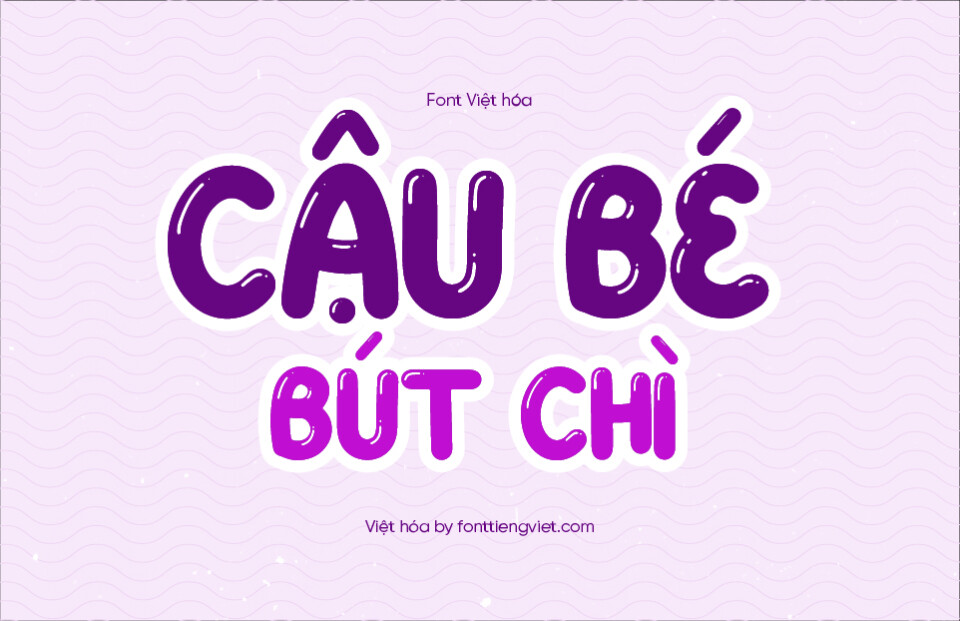
Font Việt hóa 1FTV VIP Balloon Dreams – Font bong bóng
Font Việt hóa 1FTV VIP Balloon Dreams – Font bong bóng cho thiết kế sáng tạo
Giới thiệu về Font Việt hóa 1FTV VIP Balloon Dreams – Font bong bóng
Trong thế giới đồ họa hiện đại, việc tìm kiếm một Font Miễn Phí mang phong cách vui nhộn và trẻ trung luôn là ưu tiên hàng đầu của các nhà thiết kế. Font Việt hóa 1FTV VIP Balloon Dreams – Font bong bóng là một lựa chọn hoàn hảo, mang đến hơi thở mới lạ với những đường nét mô phỏng hình dáng của những quả bong bóng căng tròn. Bộ font này không chỉ dừng lại ở tính thẩm mỹ mà còn được tối ưu hóa hoàn toàn cho tiếng Việt, giúp người dùng dễ dàng truyền tải thông điệp một cách sinh động nhất.
Đặc điểm nổi bật của bộ Font Việt hóa 1FTV VIP Balloon Dreams – Font bong bóng
Phong cách thiết kế độc đáo và linh hoạt
Đúng như tên gọi, Font Việt hóa 1FTV VIP Balloon Dreams – Font bong bóng sở hữu các ký tự có độ cong mềm mại, tạo cảm giác thân thiện và gần gũi. Kiểu chữ này cực kỳ phù hợp cho các dự án liên quan đến trẻ em, thiệp mời sinh nhật, hoặc các bìa sách giáo khoa cấp tiểu học. Sự kết hợp giữa nét chữ đậm và các góc bo tròn giúp văn bản trở nên nổi bật trên mọi nền màu sắc khác nhau, giúp các bạn học sinh dễ dàng tiếp cận nội dung bài học một cách thú vị hơn.
Tính ứng dụng thực tế trong giáo dục và đời sống
Với khả năng hiển thị tốt trên cả nền tảng kỹ thuật số và in ấn, bộ font này thường được dùng để thiết kế poster sự kiện trường học hoặc các biển báo trang trí lớp học. Việc sử dụng Font Việt hóa 1FTV VIP Balloon Dreams – Font bong bóng giúp không gian học tập trở nên tràn đầy năng lượng và kích thích sự sáng tạo của người xem.
Kết luận về bộ chữ bong bóng ấn tượng